魏碑体是一种很有特点的字体,它有点古文的蕴意在里面,不像宋体这样的规范,但是特别的美观。我国古代文化博大精深,尤其中国的汉字在全世界范围内都很有名,这种代表着我国古色古香的汉字真的是很有魅力的,但是魏碑字体大全往往运用的不是很普遍,只是极个别爱好者在某些铁特定的情况下才使用的。那么魏碑字体大全究竟可以用在哪?
因为魏碑字体是很有古韵的字体,而古诗也是在古代非常盛行的。尽管现代人也有喜欢古诗的,但是毕竟现代人已经很少对古诗特别感兴趣了,这只能说是一部分小团体的爱好了。而现在网络的流行让一些人喜欢直接在网络上创造,这是如果用魏碑字写的话就会使古诗读起来特别的有感觉,增加古诗的味道。
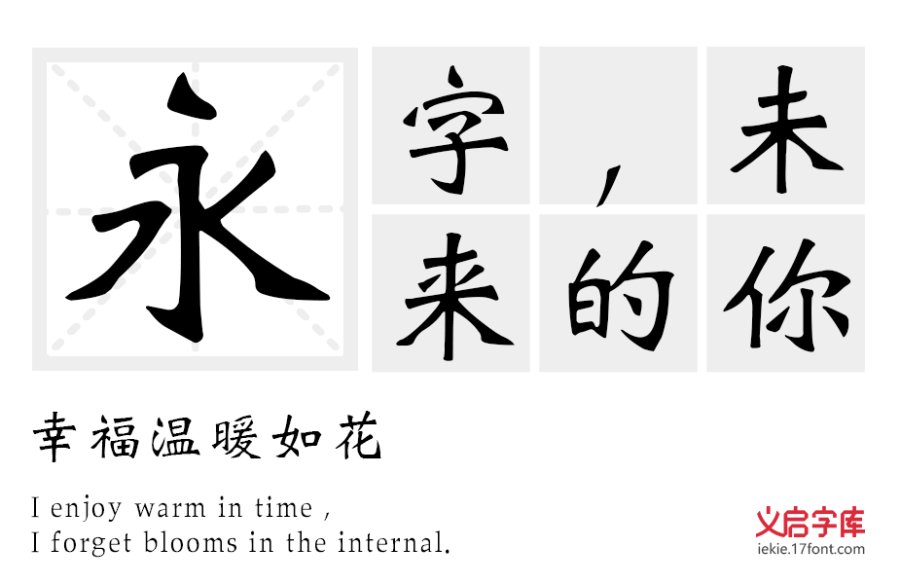
现代人很多都特别喜欢看古典小说,与现代小说的快节奏相比,古典小说读着让人觉得缓缓悠长,古色古香的文章在现代气息中读着别有一番味道。而一些小说创作者喜欢运用魏碑字体这样同样古典的字体来写小说,这样会让读着更加感觉到自己被带入了古代跟着小说中的人物一起参与他们的故事,这种感觉会很奇妙的。
我们都知道在文章中插入一些格言会给文章加分,那么我们在插入一些格言的时候可以运用魏碑字体,这样不仅让格言在文章中更醒目,而且会瞬间提升格言给人的感觉,就如同瞬间给自己敲响警钟的感觉一样。